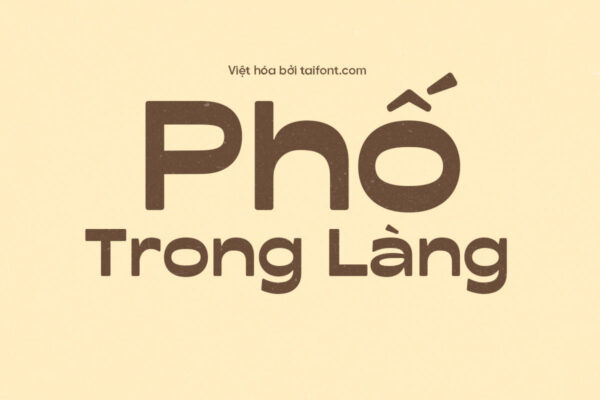
Giới thiệu về Font TF Gafiton Rounded Việt hóa
TF Gafiton Rounded Việt hóa là một font chữ không chân (sans-serif) được biến tấu từ phiên bản Gafiton gốc, nổi bật với nét dày, độc đáo và các góc bo tròn mềm mại. Sự kết hợp giữa nét mạnh mẽ của Gafiton và sự thân thiện của các góc bo tròn tạo nên một phong cách vừa cá tính, hiện đại, lại vừa dễ chịu và gần gũi.
Font này là lựa chọn lý tưởng cho các thiết kế muốn truyền tải sự nổi bật, độc đáo nhưng vẫn mang vẻ thân thiện và dễ tiếp cận:
- Thiết kế đồ ăn và ẩm thực: Hoàn hảo cho menu, bao bì sản phẩm thực phẩm, poster quảng cáo món ăn, hoặc các ấn phẩm truyền thông liên quan đến ẩm thực. Nét dày bo tròn gợi cảm giác ngon miệng, ấm cúng và hiện đại, giúp món ăn thêm hấp dẫn.
- Tiêu đề và in ấn: Phù hợp cho các tiêu đề chính trên website, banner, poster, hoặc các ấn phẩm in ấn cần sự rõ ràng và ấn tượng. Font này đảm bảo thông điệp của bạn luôn được đọc rõ và gây chú ý.
- Thiết kế cho trẻ em: Mang lại vẻ vui tươi, ngộ nghĩnh và thân thiện cho các sản phẩm, ấn phẩm dành cho trẻ em, giúp thu hút sự chú ý của các bé.
Với TF Gafiton Rounded Việt hóa, bạn có thể dễ dàng thổi hồn sáng tạo, sự độc đáo và nét thân thiện vào các thiết kế, tạo ra những sản phẩm không chỉ đẹp mắt mà còn rất ấn tượng và mang đậm dấu ấn riêng.
Font Việt hóa TF Gafiton Rounded